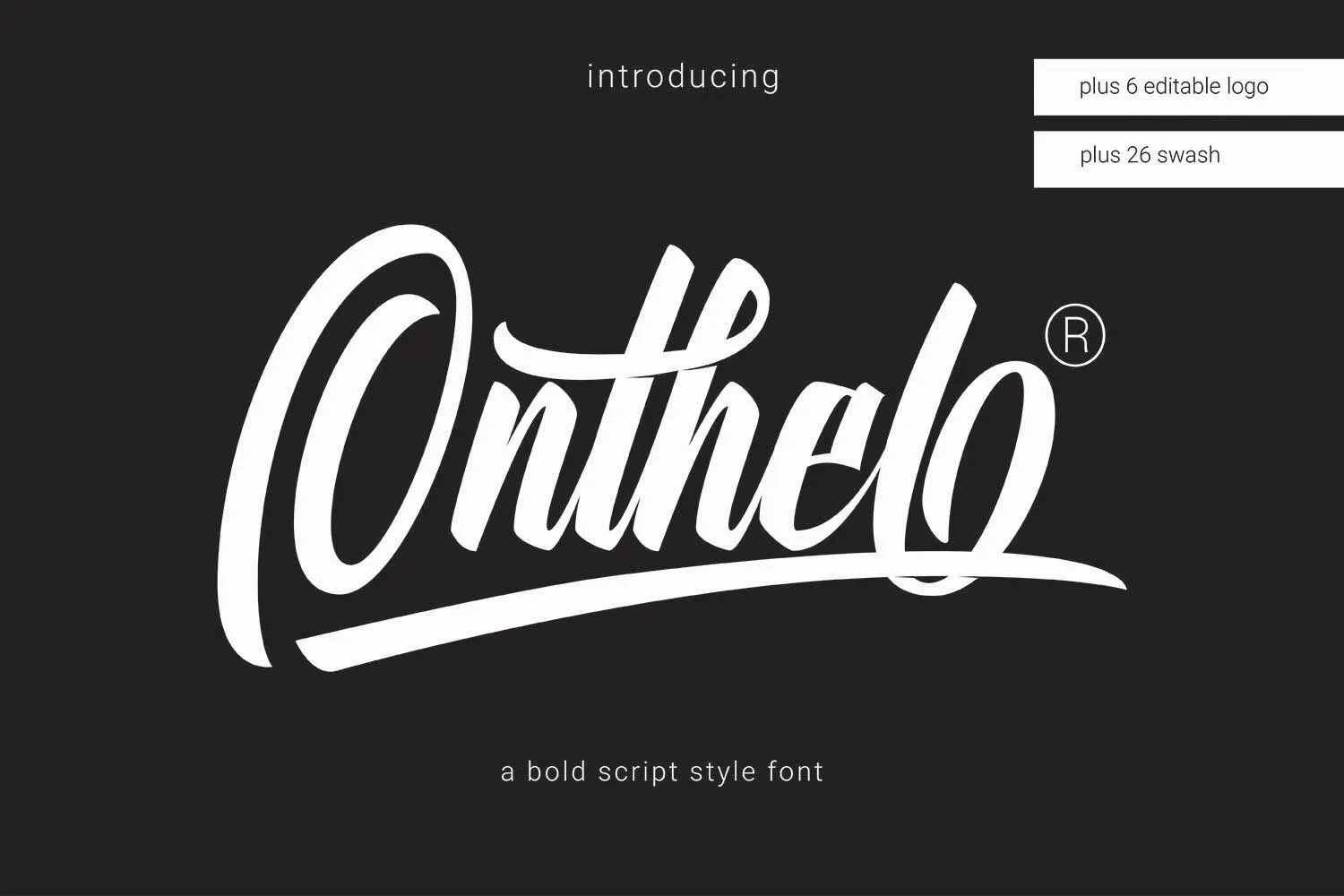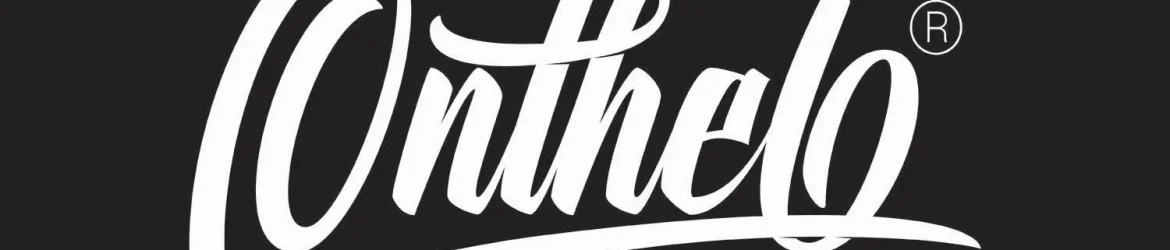
Introduzimos a Onthel Font, uma nova fonte script bold. Esta fonte pode ajudar você a criar designs perfeitos e únicos. Ela foi criada por Grayscale. A Onthel é um script forte com toques de esquadração que são adoráveis e têm personalidade. Inspirada nas bicicletas Onthel, designadas na Holanda conhecidas pela posição assentamento vertical e uma reputação muito forte e de alta qualidade. Este site tem tudo a ver para quem está procurando por um estilo elegante e sofisticado para seus projetos gráficos, seja ele em cartazes publicitários ou materiais de design digital. Descubra o charme inegável da Onthel Font.